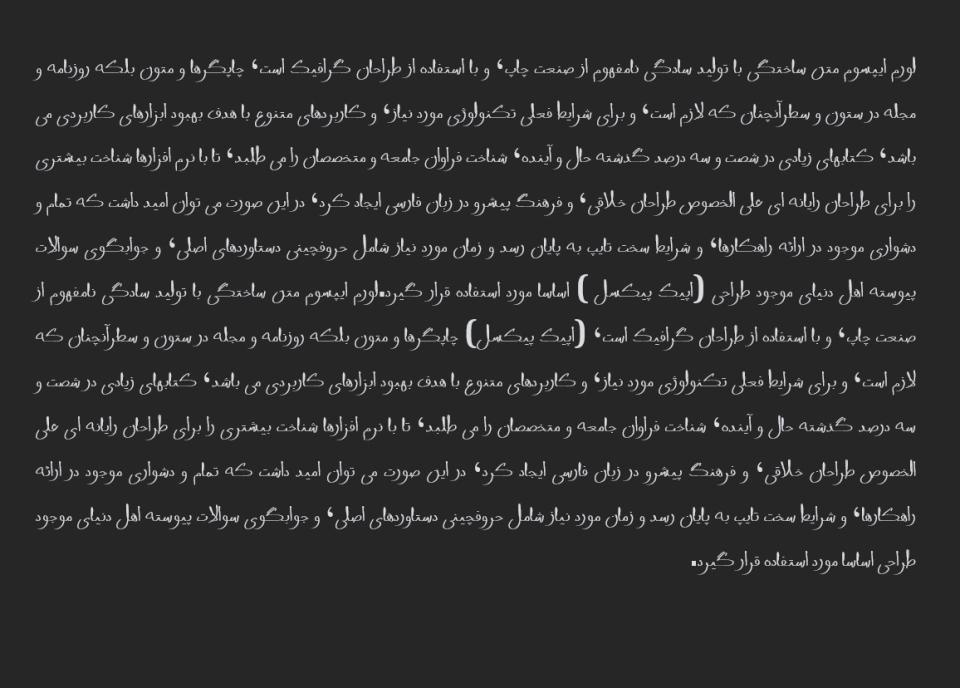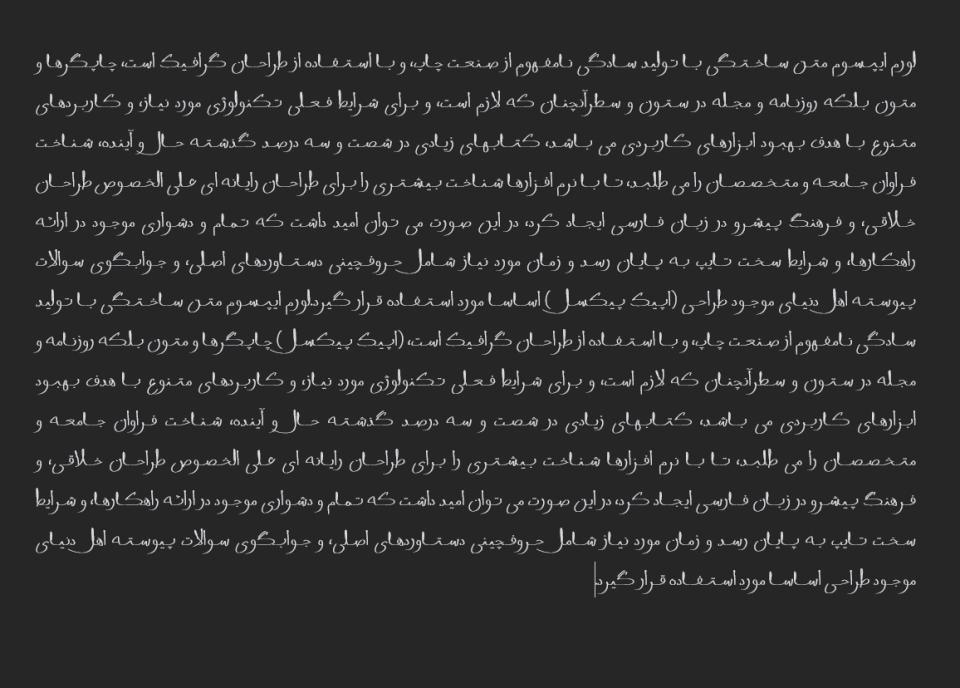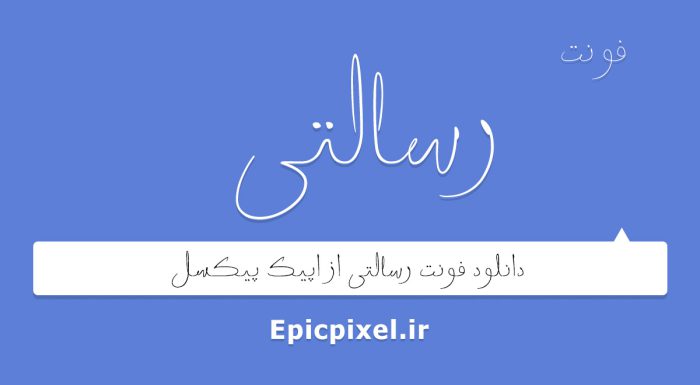
2 فونت رسالتی فارسی Resalaty
فونت رسالتی فارسی، یک انتخاب ایده آل برای کسانی است که به دنبال حسی نوستالژیک و صمیمانه در طراحی های خود هستند. این فونت رایگان، با ظاهری دست نویس و روان، درست مانند نوشته ای با خودکار بر روی کاغذ، به آثار شما روحی تازه می بخشد.
یکی از ویژگی های برجسته این فونت، خوانایی بالای آن در اندازه های مختلف است؛ چه در عناوین بزرگ و چه در متن های کوتاه، حروف به خوبی از هم تفکیک شده و چشم را خسته نمی کنند. این ویژگی، فونت رسالتی را برای استفاده در طراحی های چاپی مانند پوسترها و بروشورها و همچنین طراحی های دیجیتال مانند وبسایت ها و شبکه های اجتماعی مناسب می سازد.
حالت فونت دست نویس این فونت، به طراحی ها صمیمیت و گرمایی خاص می بخشد و حس نزدیکی بیشتری با مخاطب ایجاد می کند. این ویژگی به خصوص برای طراحی هایی با موضوعات فرهنگی، هنری، ادبی و حتی شخصی، بسیار کارآمد است. با این حال، باید توجه داشت که استفاده بیش از حد از این فونت در متون طولانی ممکن است کمی خسته کننده باشد، زیرا حالت دست نویس آن، ریتم متفاوتی نسبت به فونت های رسمی تر دارد.
فونت رسالتی، با وجود سادگی، از ظرافت خاصی نیز برخوردار است. انحنای نرم حروف و اتصالات طبیعی بین آن ها، حس یک نوشته واقعی را القا می کند. این ویژگی، فونت را از سایر فونت های دست نویس متمایز می کند و به آن شخصیتی منحصربه فرد می بخشد. اگر به دنبال فونتی هستید که هم رایگان باشد، هم حس اصالت و صمیمیت را به طراحی های شما ببخشد و هم خوانایی مناسبی داشته باشد، فونت رسالتی فارسی گزینه ای عالی برای شماست.